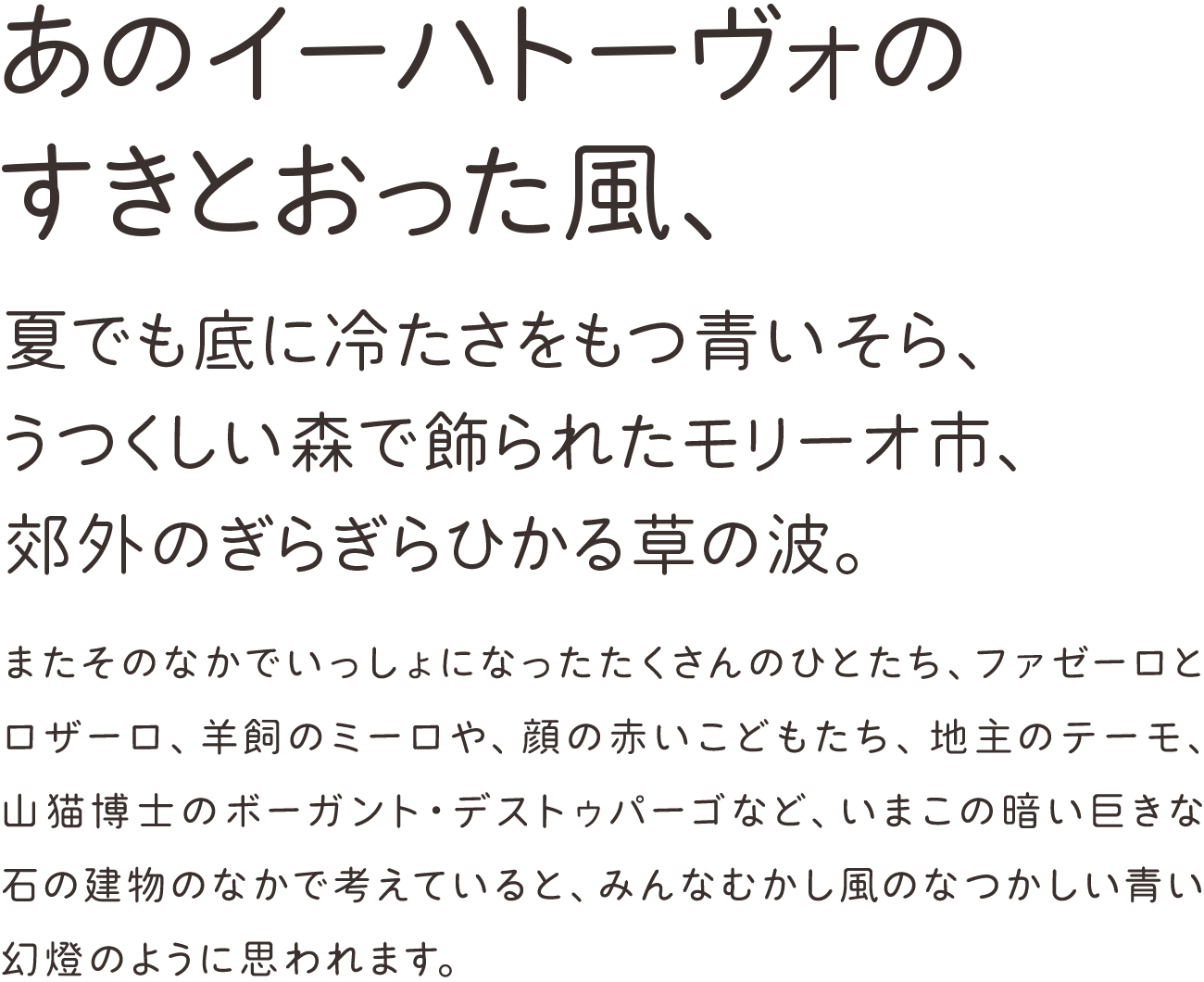
丸丸ゴシックASr
3種類のかなと2種類の角丸で使い分けができる、やさしくてかわいい丸ゴシック体フォント。「A」は明るい印象で、「B」はクセが少なく、「C」は落ち着きのあるデザイン。漢字は共通で、小さめカーブの「Sr」とゆったりカーブの「Lr」が用意されています。
• 丸丸ゴシックASr
丸丸ゴシックASr
• 丸丸ゴシックALr
丸丸ゴシックALr
B
C
※かなのデザインが違う3種類のシリーズ。漢字はカーブの小さいSrと大きいLrが用意されています。